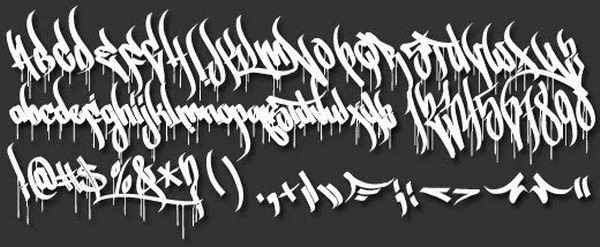
Sprite Graffiti
Шрифт Sprite Graffiti относится к категории рукописные.
Гарнитура содержит 3 начертания. Поддерживает 12 языков.
Автор
Arsek & Erase,
Font family: Sprite Graffiti
Manufacturer name: Arsek Erase